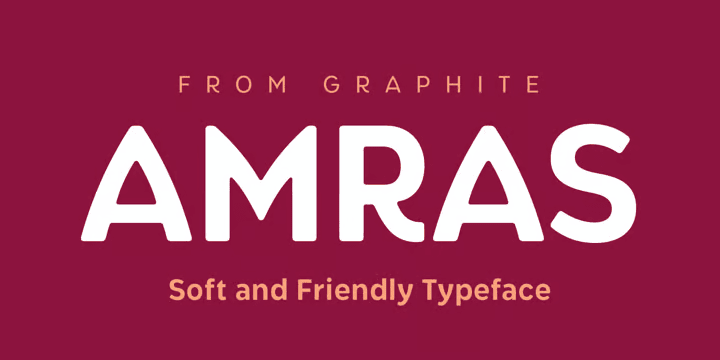
Amras
ソフトでフレンドリーなサンセリフディスプレイ。柔らかな印象のポップなサンセリフで、アウトラインの角が丸くなっているほか、斜めのストロークがくっと曲がってアーチ状になっているのが特徴。A や R など頭でっかちなプロポーションがかわいらしさを演出している。子供向けや食品・スイーツなどと相性が良さそう。イタリックはないが8ウェイトあり。ただいま30%オフセール中。